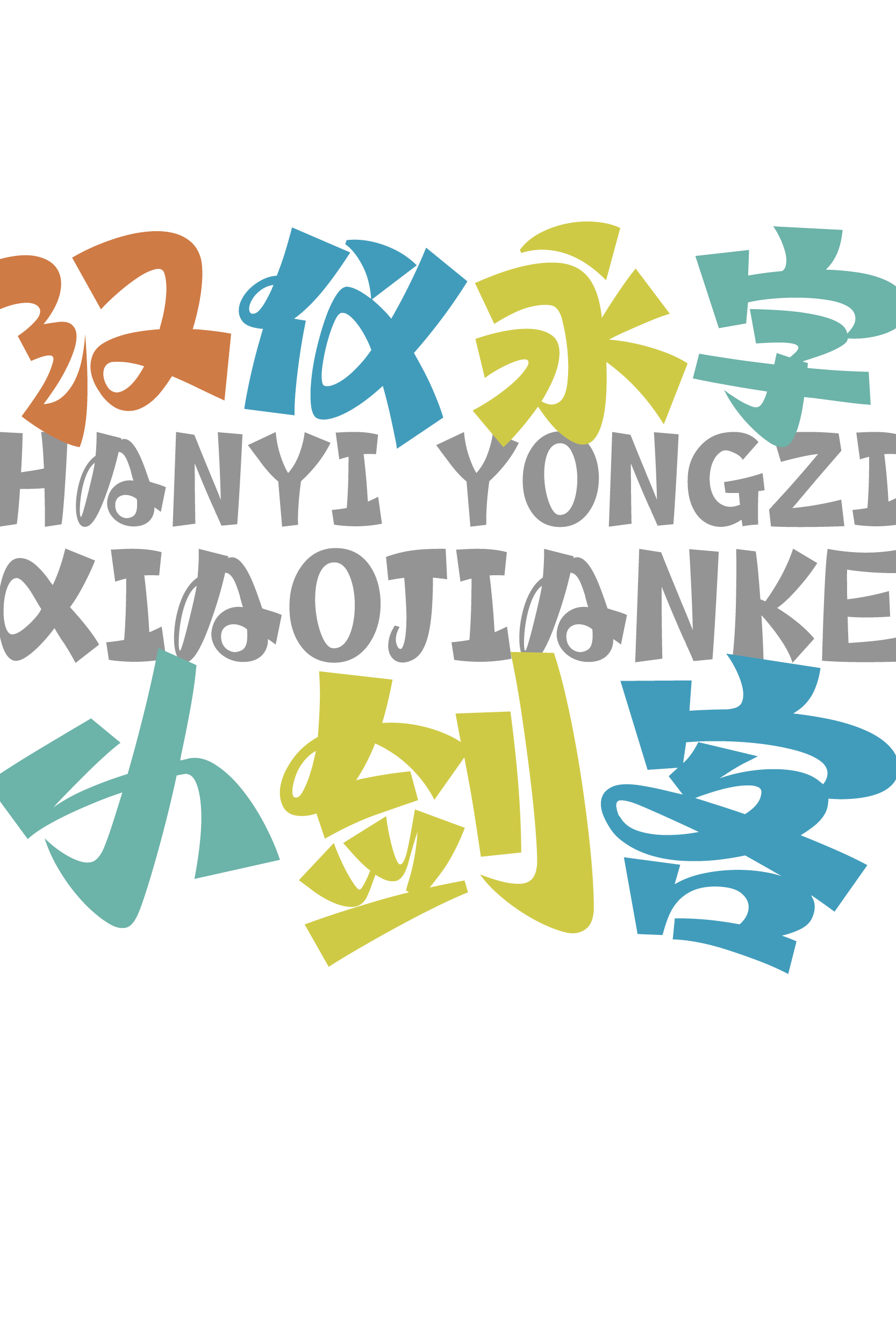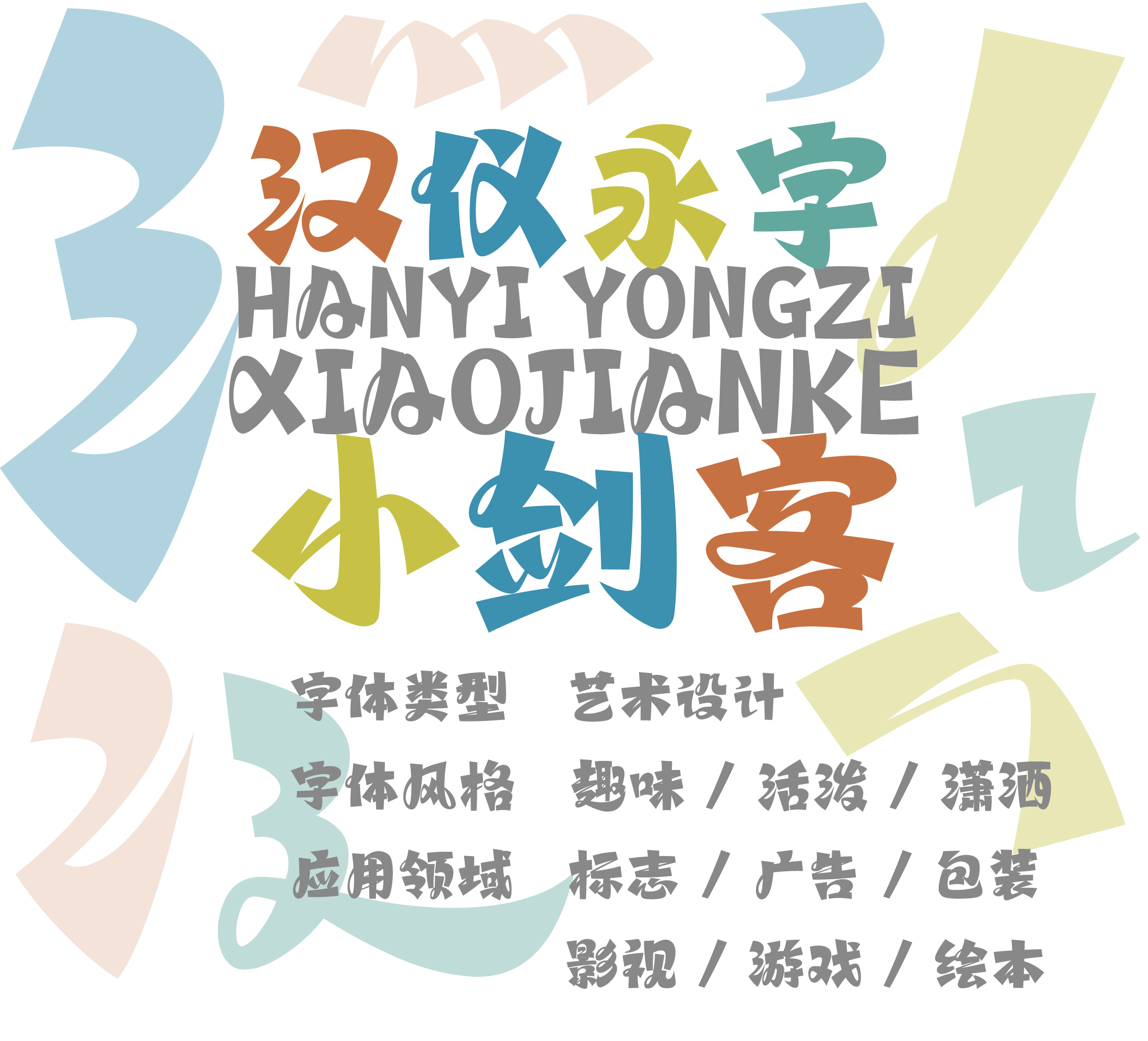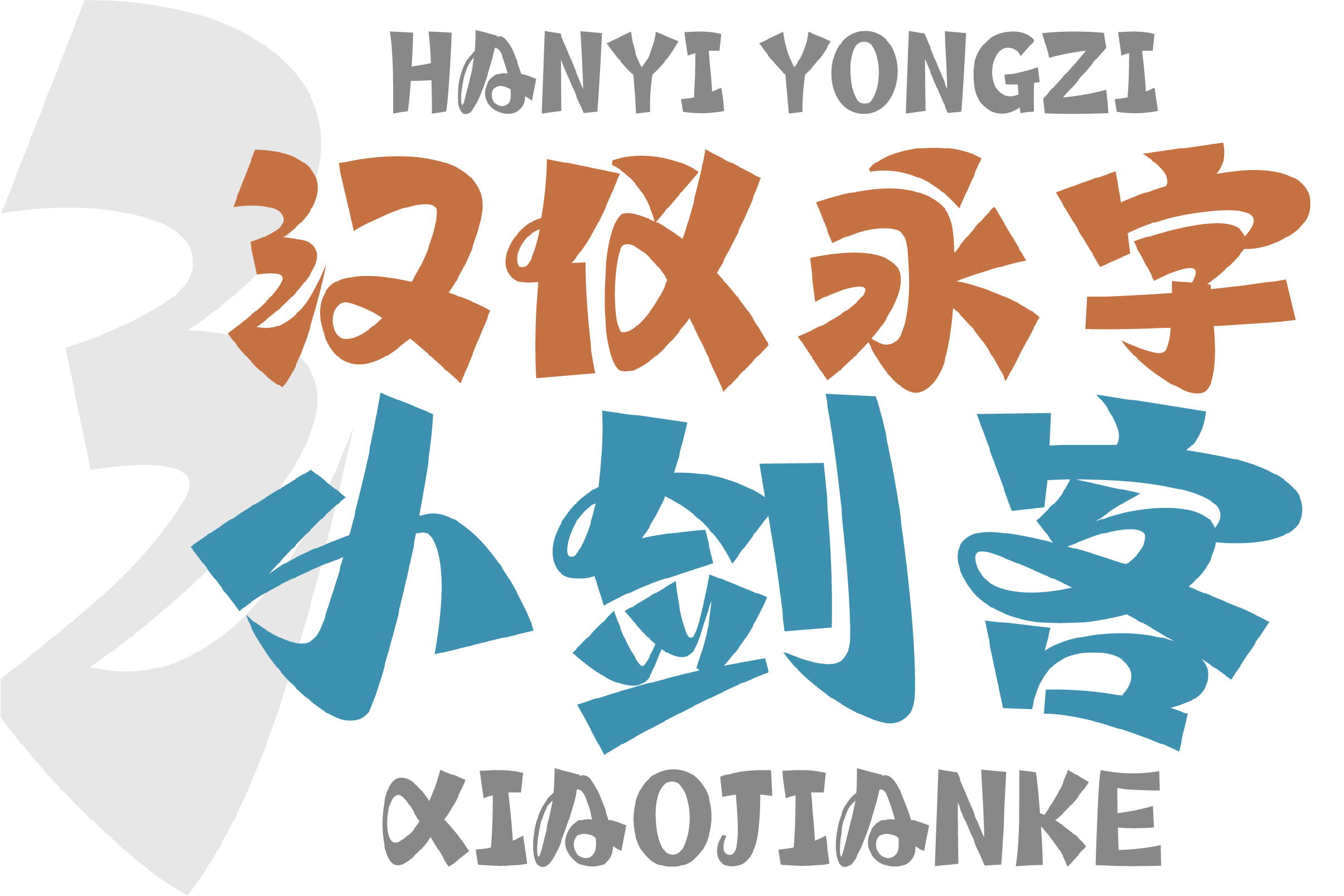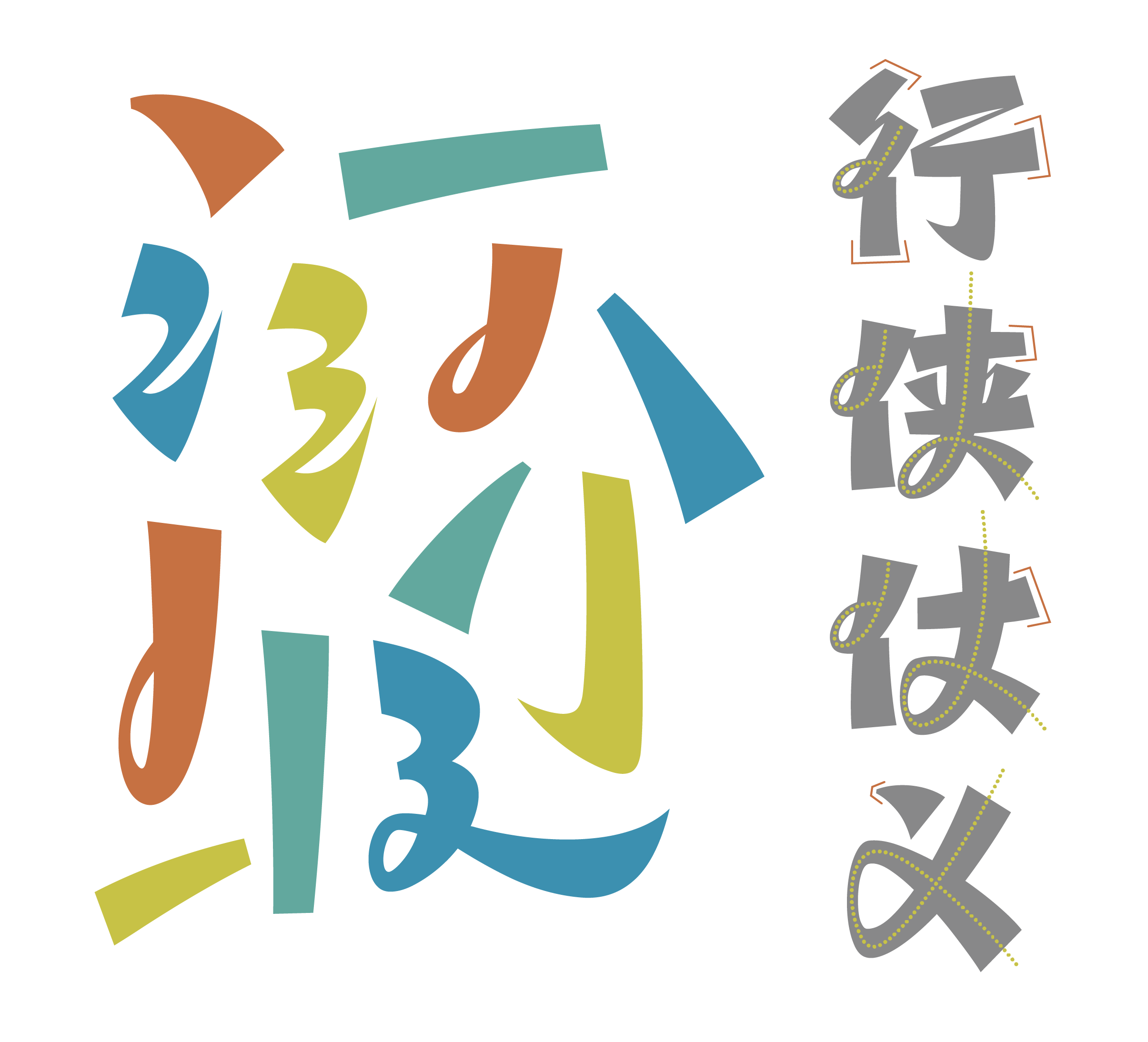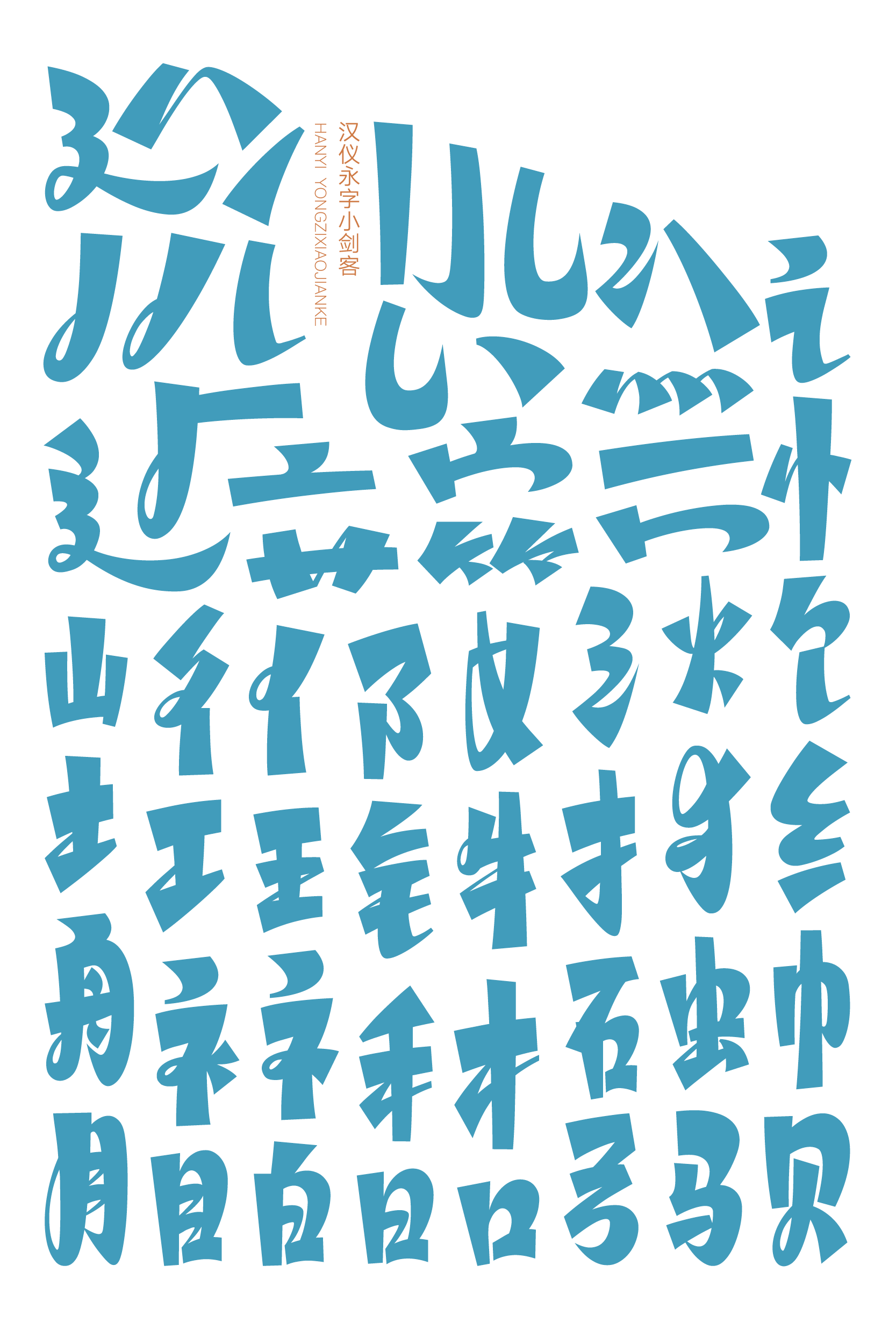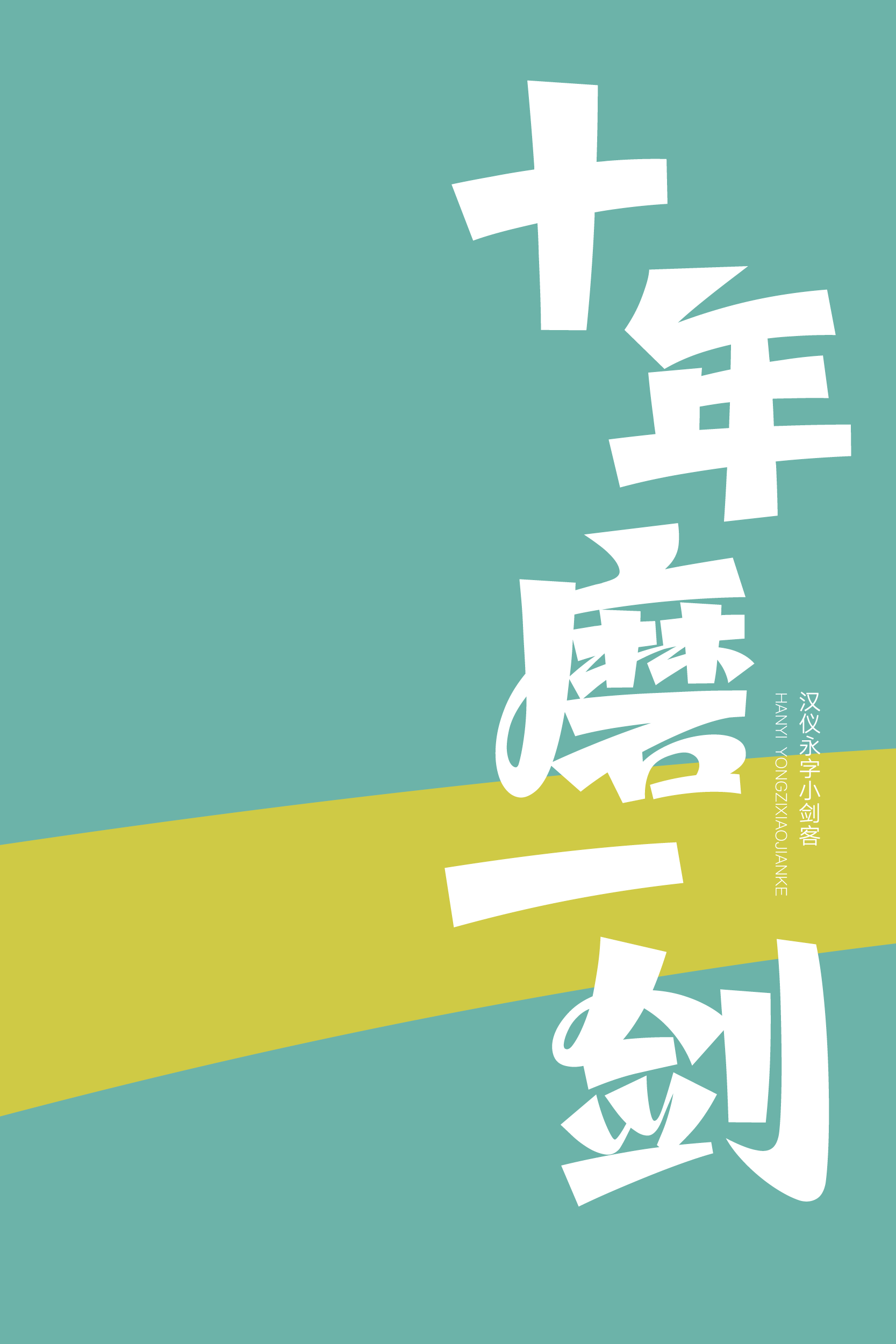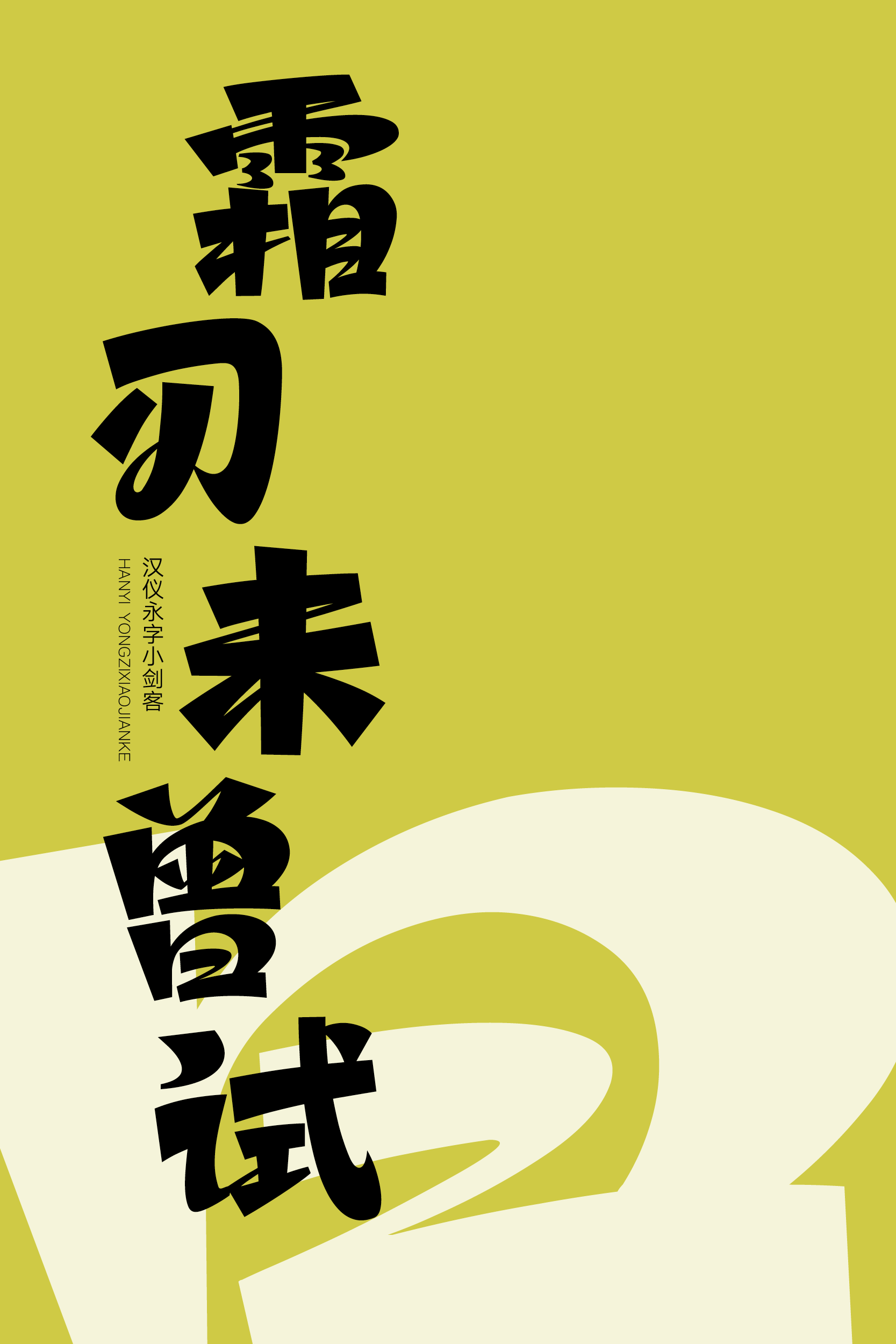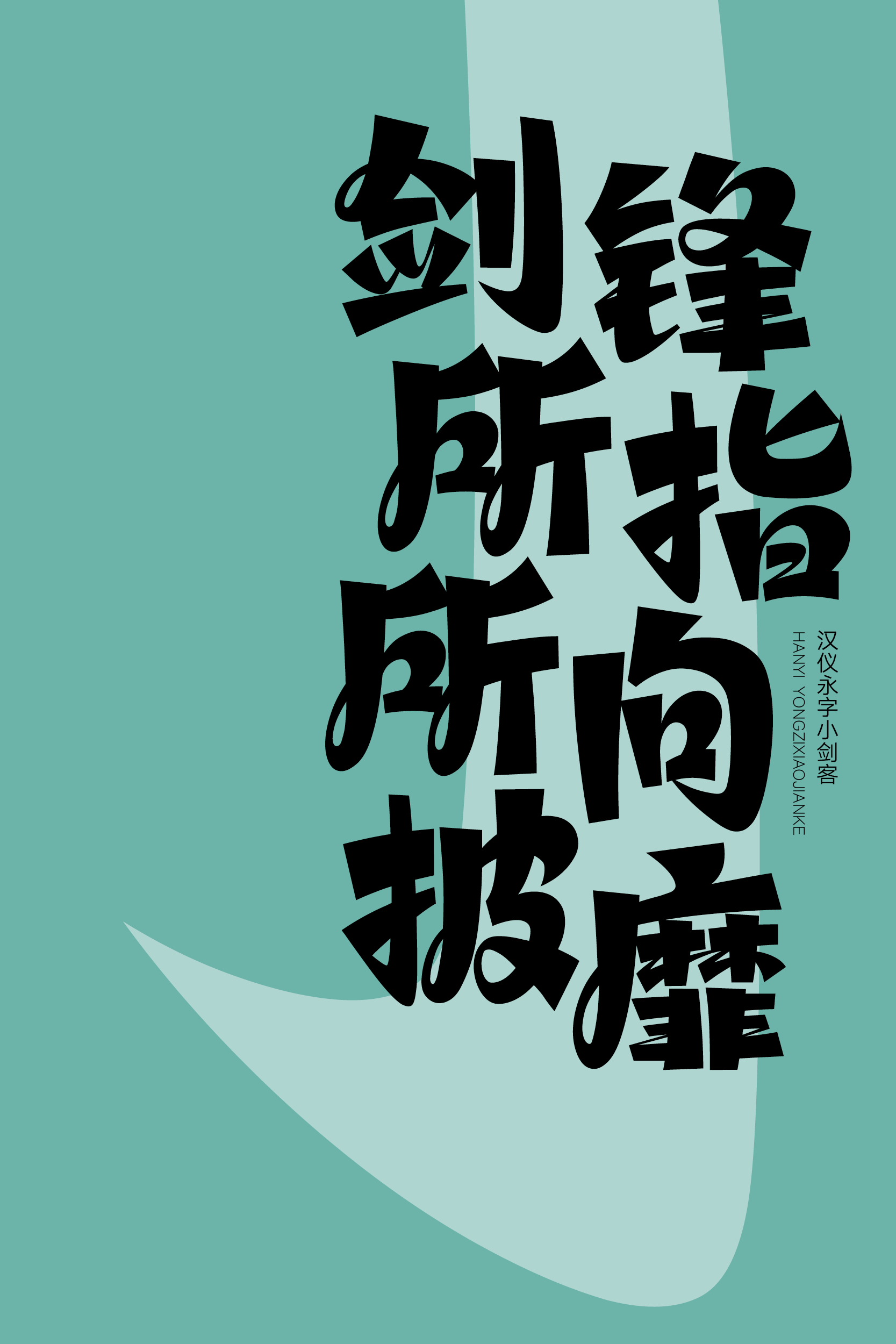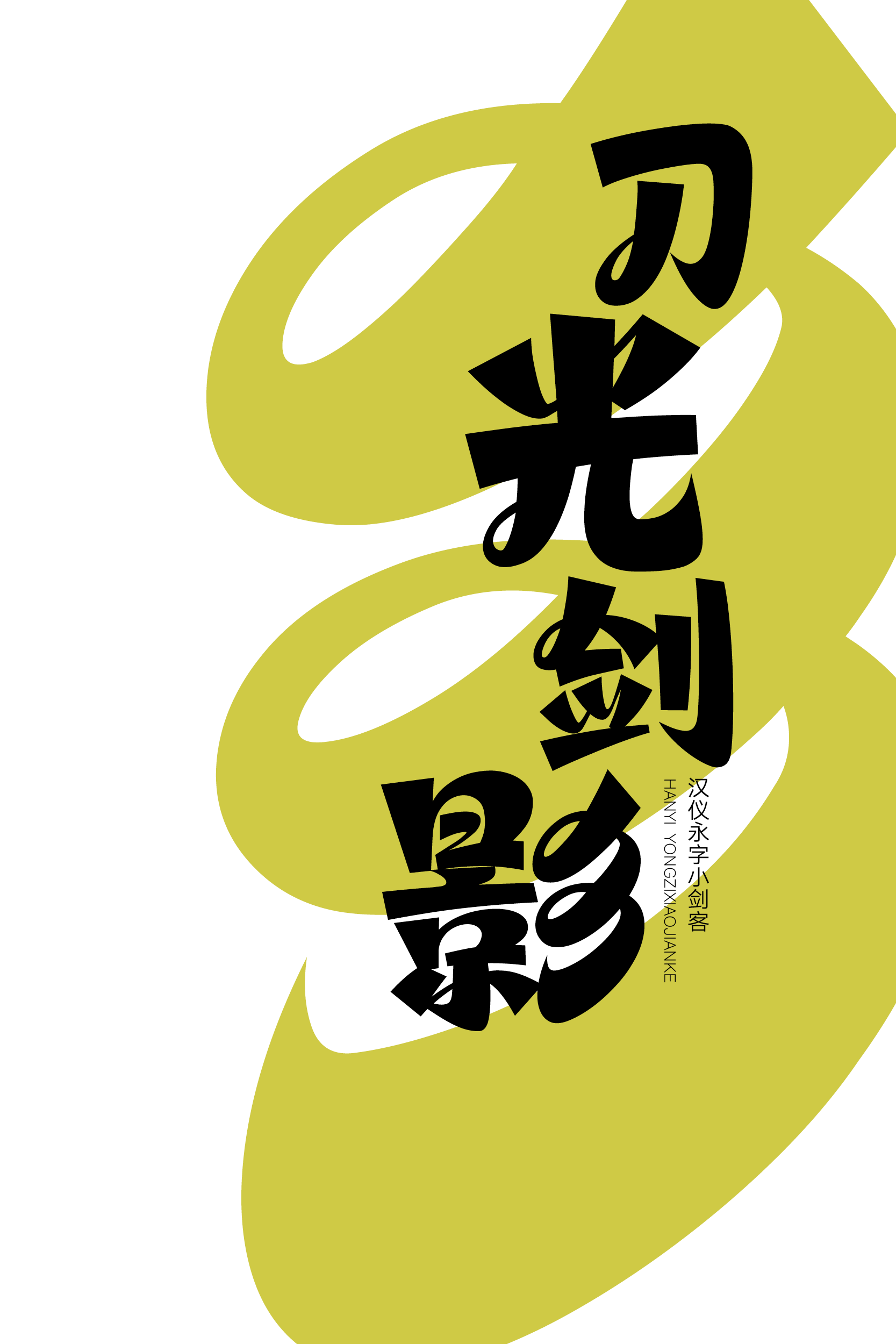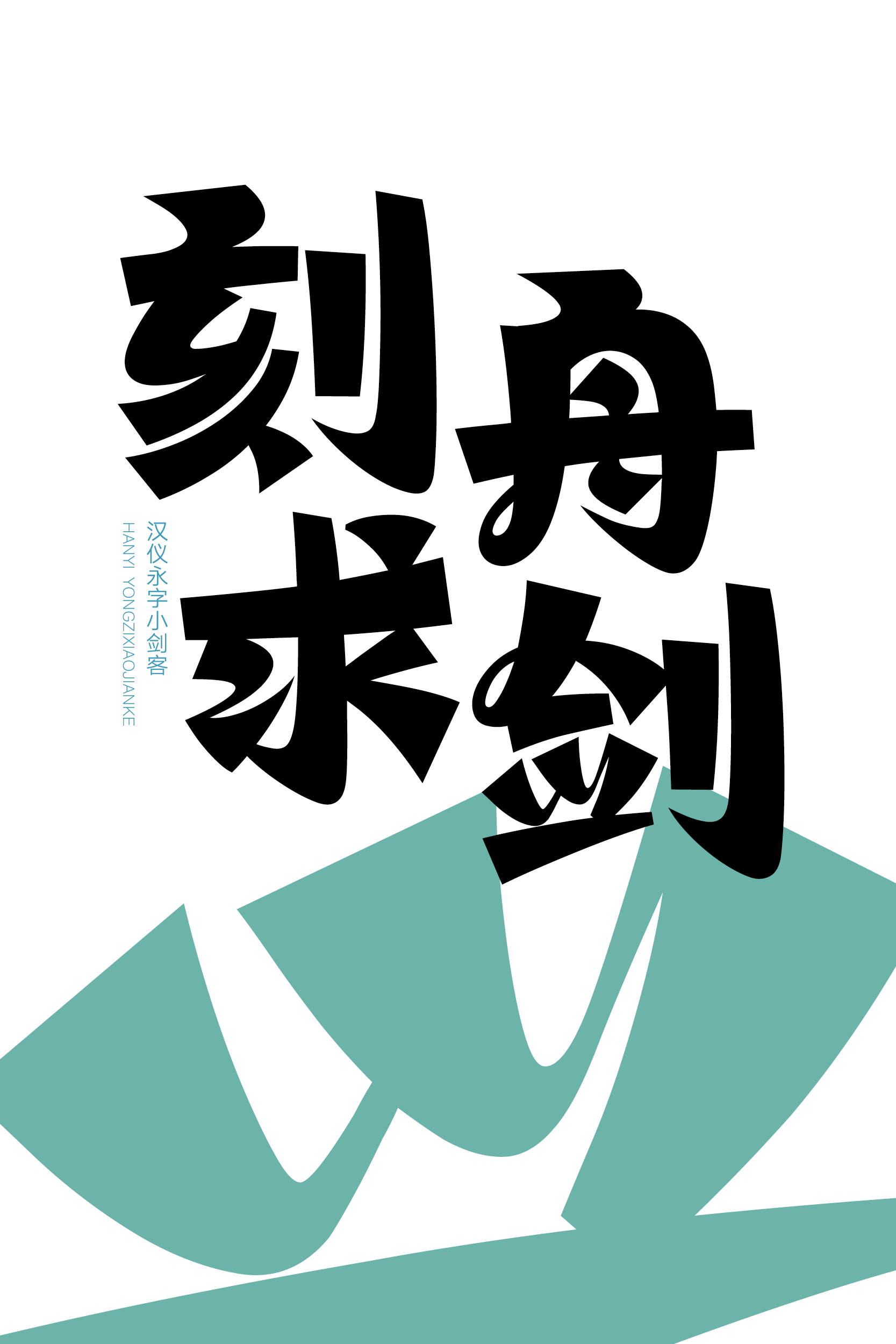
汉仪永字小剑客
汉仪永字小剑客,平稳之中有跃动感,曲直相映,富有张力。笔画如挥剑般潇洒自如,一气呵成;牵丝和断连相映,似刀光剑影。这款字体由永字社创作,适合作为标题字体应用于产品包装、影视游戏、书籍绘本等使用场景,汉仪永字小剑客,剑锋所指,所向披靡。
字形饱满,平稳之中带有跃动感。
方而粗的笔画一气呵成,弧线连笔流畅潇洒。
笔画的牵丝、断连、搭接处理形成跃动的节奏。
西文部分像是小剑客潇洒自如挥剑而成,连贯而有力。